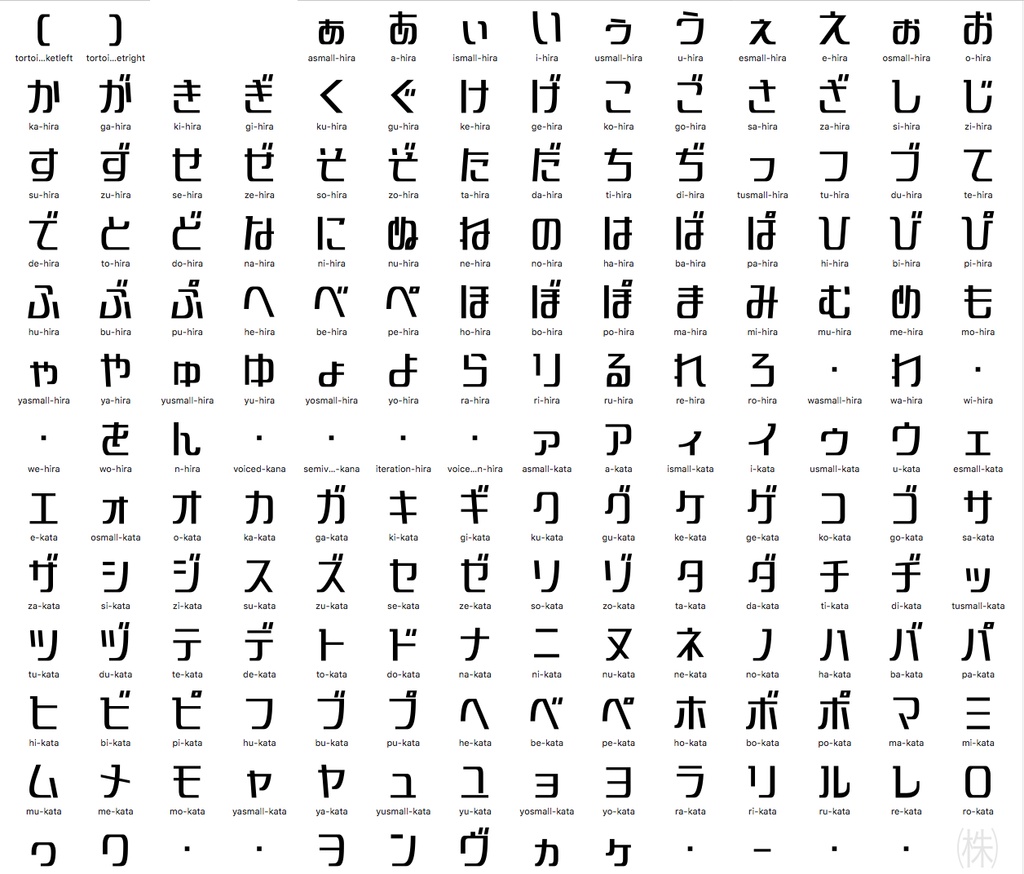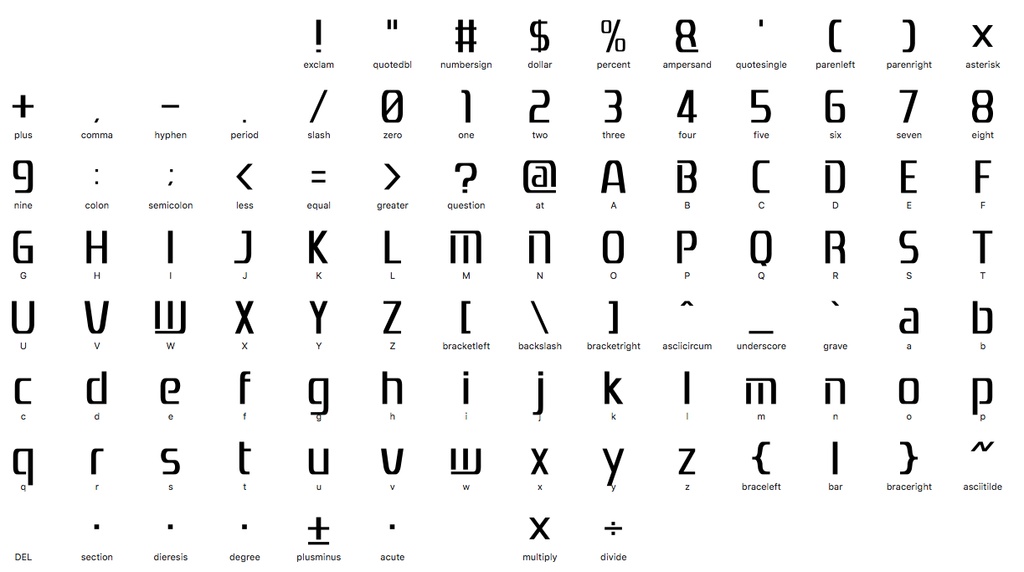
■フォントの日まで半額セール(500円→250円) ポラリス フォントは、新しい雰囲気のゴシック体。ハイセンスなひらがな・カタカナに、シャープな印象のアルファベットを加えました。垂直水平のシャープなデザインと、かわいいアールの組み合わせが幅広いデザインにマッチします。 動作環境 Mac:システム/OS X対応(10.x)〜最新のOS X Windows:OS/日本語版Windows2000、XP、VISTA、Windows7〜11以降 フォント形式:TrueTypeフォント 収録文字数について ひらがな、カタカナ、アルファベットのみの書体になります。 安心して使えるロイヤリティフリーの書体 あらゆる商用・デザイン用途(印刷物・ゲーム・アプリ・映像・動画・ロゴ・同人作品)に使用できる、商用申請の必要のないロイヤリティフリーの書体になります。文字の加工・変形も可能です。ご安心ください。 個性的なデザインに注目した日本語フォントのダウンロード販売。物語の奥行きを感じさせるセンスの良いフォントは、あなたのデザインに深みとおもしろみを与えます。安心して使える商用利用可のオリジナルフォントです。 1商品(1ライセンス)につき1ユーザー1PCのみがご利用いただけます。複数人で使用する場合は人数分をご購入ください。